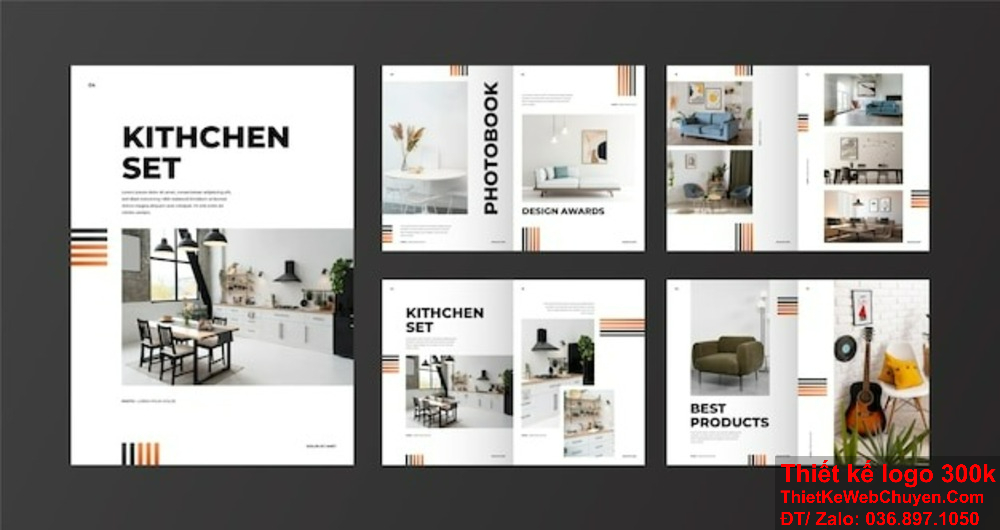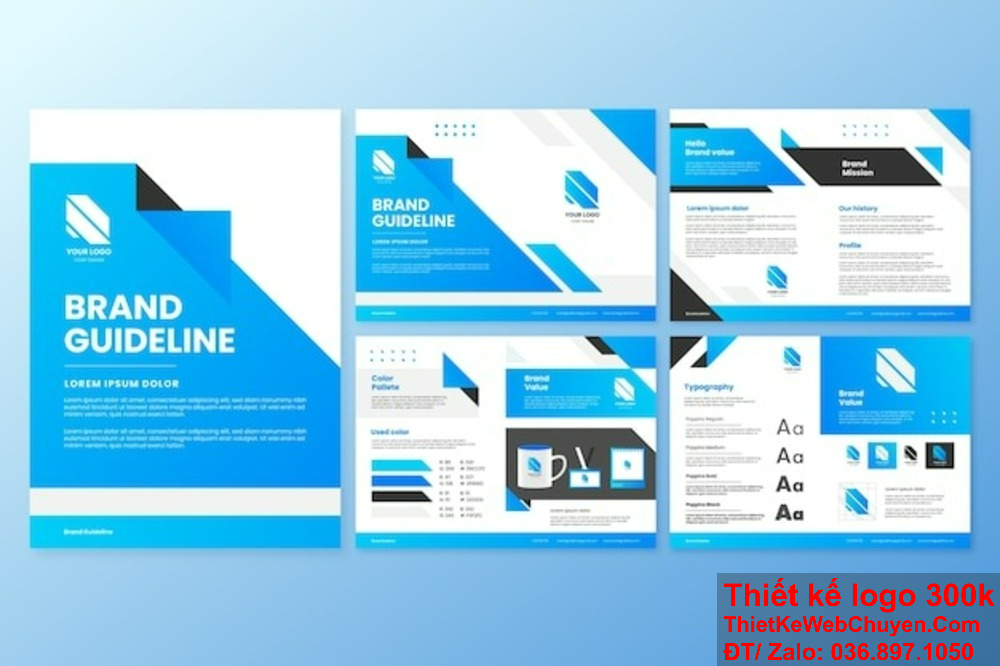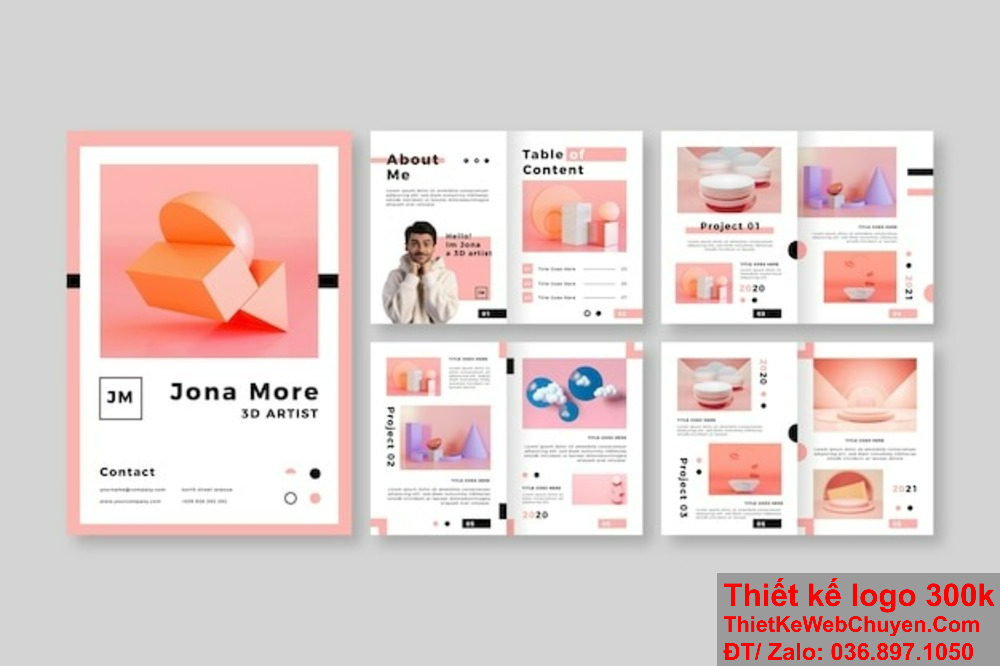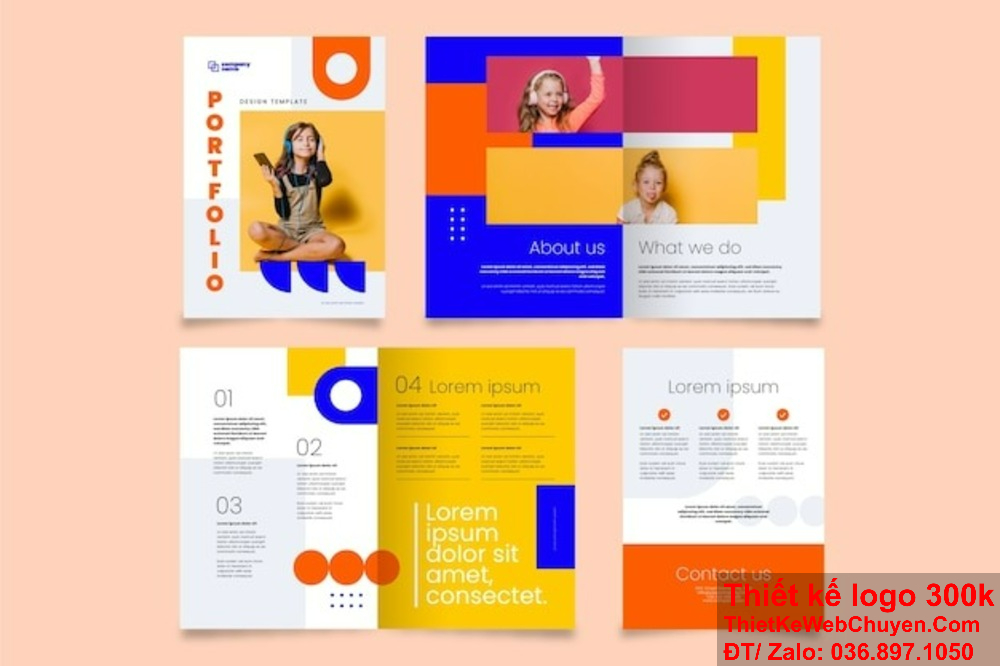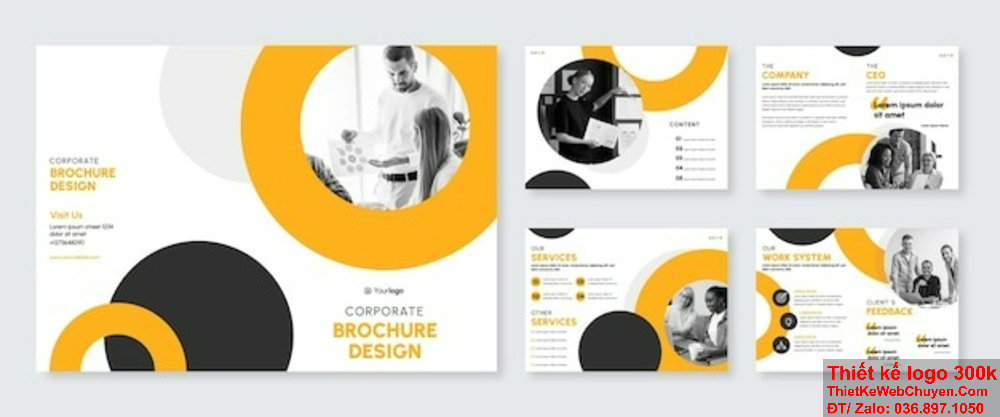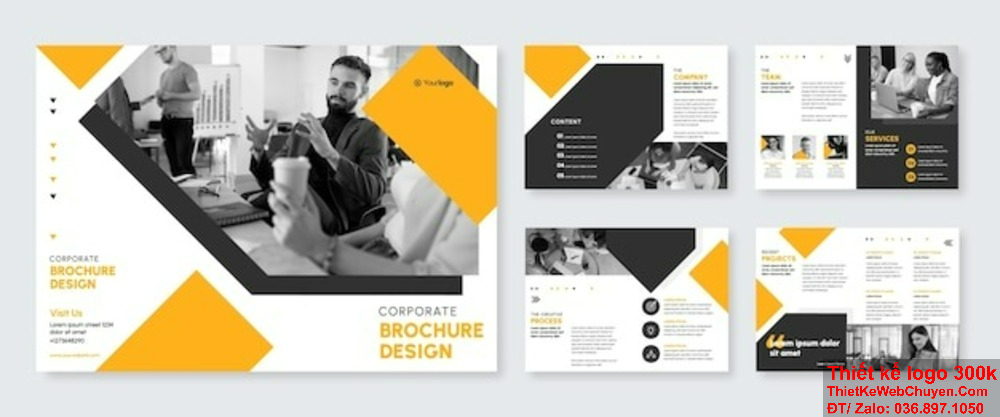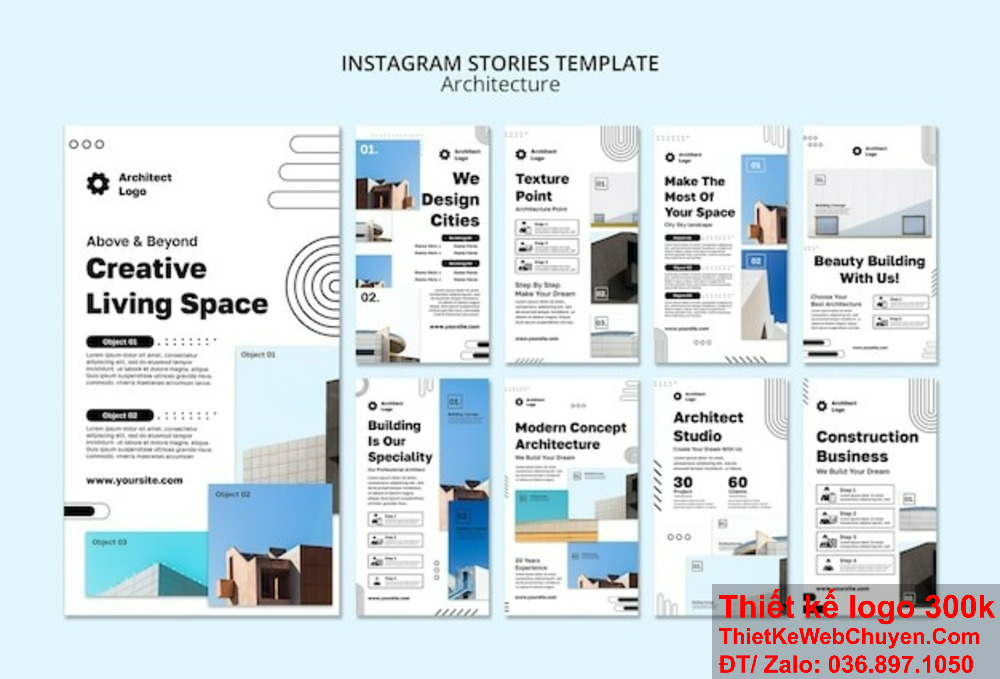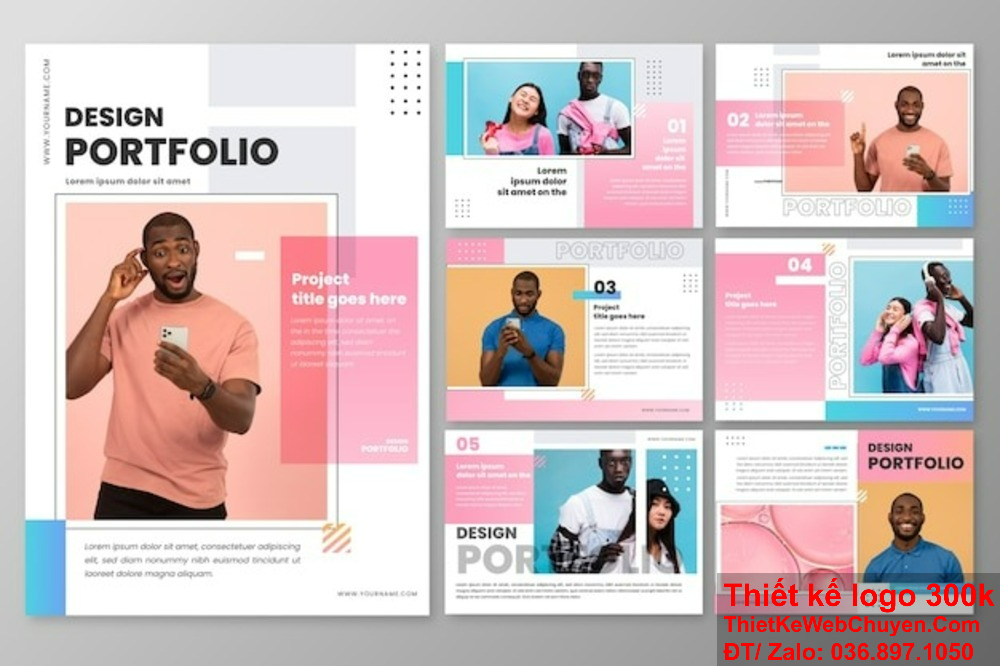
Font chữ trong thiết kế profile đóng vai trò quan trọng trong việc thiết kế profile, đó là cầu nối giữa nội dung và người xem, góp phần quyết định về ấn tượng ban đầu. Font chữ trong thiết kế profile không chỉ đơn thuần là những ký tự trên màn hình mà còn là ngôn ngữ thị giác, truyền đạt không chỉ thông điệp mà còn cả tâm trạng và cá nhân của người sử dụng font chữ trong thiết kế profile.
Giới Thiệu Chủ Đề Font Chữ Trong Thiết Kế Profile
Đầu tiên, font chữ trong thiết kế profile có thể được định nghĩa như bộ ký tự chung với kiểu dáng và đặc tính nhất định. Mỗi font chữ trong thiết kế profile mang đến một cái nhìn riêng biệt, từ những đường cong mềm mại của serif đến sự hiện đại và gọn gàng của sans-serif. Vai trò của font không chỉ giới hạn ở khả năng truyền đạt thông điệp mà còn mở rộng đến việc tạo nên sự chuyên nghiệp, sáng tạo, hay thậm chí là tính cá nhân của người sử dụng profile.
Sự ảnh hưởng của font là không thể phủ nhận. Ngay từ cái nhìn đầu tiên, font chữ trong thiết kế profile tạo ra ấn tượng mạnh mẽ và nhanh chóng hình thành một hình ảnh về người sử dụng. Sự chọn lựa cẩn thận về font chữ trong thiết kế profile có thể nói lên tính cách, phong cách và mục tiêu của cá nhân đó. Một font phù hợp không chỉ làm tăng giá trị thẩm mỹ mà còn là yếu tố quyết định sự chuyên nghiệp và độ chân thực của thông điệp được truyền đạt.
Tổng kết, font chữ trong thiết kế profile là một phần không thể thiếu trong việc xây dựng hình ảnh cá nhân trên các nền tảng trực tuyến. Từ việc chọn lựa kiểu dáng đến màu sắc, mỗi quyết định về font đều ảnh hưởng đến cách mà người xem đánh giá và nhớ đến một profile. Chính vì vậy, hiểu rõ và sử dụng đúng font chữ trong thiết kế profile là chìa khóa để tạo nên một ấn tượng mạnh mẽ và lâu dài trong không gian trực tuyến ngày nay.
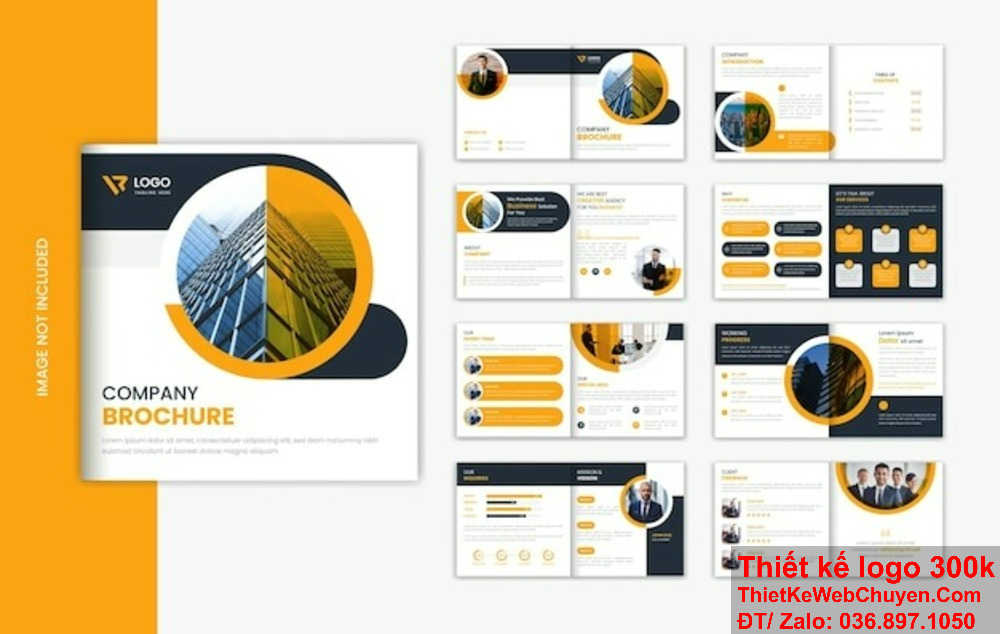
Lịch Sử Phát Triển Font Chữ Trong Thiết Kế Profile
Lịch sử phát triển font là một hành trình đầy màu sắc và sáng tạo, từ những bước đầu tiên của chữ viết tay đến sự đa dạng và phong phú của font chữ trong thiết kế profile kỹ thuật số ngày nay. Các bước quan trọng trong lịch sử này đã ảnh hưởng đến cách chúng ta hiểu và sử dụng font.
Bắt đầu từ thời kỳ cổ điển, font chữ trong thiết kế profile yếu được tạo ra thông qua việc viết tay. Đây là thời kỳ của những bức thư và tài liệu chính thức được soạn thảo bằng bàn tay tài năng của các nghệ sĩ viết chữ. Tuy nhiên, sự đòi hỏi về tốc độ và khả năng nhân bản đã thúc đẩy sự phát triển của các kiểu chữ in ấn đầu tiên.
Trong thời kỳ công nghiệp, máy in chữ đã xuất hiện, mở ra kỷ nguyên mới trong việc sản xuất và phân phối sách báo. Điều này tạo nên sự đa dạng hóa về kiểu chữ, từ serif truyền thống đến xu hướng sans-serif tiện ích. Đến thập kỷ 20, sự phổ biến của máy tính và công nghệ số hóa đã mở ra cánh cửa cho font chữ trong thiết kế profile kỹ thuật số, nơi mà người thiết kế có thể tạo ra và tùy chỉnh font một cách linh hoạt và sáng tạo.
Sự thay đổi và xu hướng trong việc sử dụng font chữ trong thiết kế profile qua các thời kỳ phản ánh cả những biến động xã hội, văn hóa và kỹ thuật. Từ sự tinh tế của chữ serif trong thời kỳ quốc gia hoá, đến sự đơn giản và hiện đại của chữ sans-serif trong thời đại công nghiệp, mỗi thời kỳ mang lại một cái nhìn mới về vẻ ngoại hình và cảm nhận về thông điệp.
Tóm lại, lịch sử phát triển font là một cuộc hành trình không ngừng, đưa chúng ta từ chữ viết tay cổ điển đến sự đa dạng và linh hoạt của font chữ trong thiết kế profile kỹ thuật số hiện đại. Hiểu rõ lịch sử này giúp chúng ta có cái nhìn sâu sắc hơn về tầm quan trọng của font chữ trong thiết kế profile trong việc thể hiện cá nhân và tạo nên ấn tượng trong thiết kế profile.
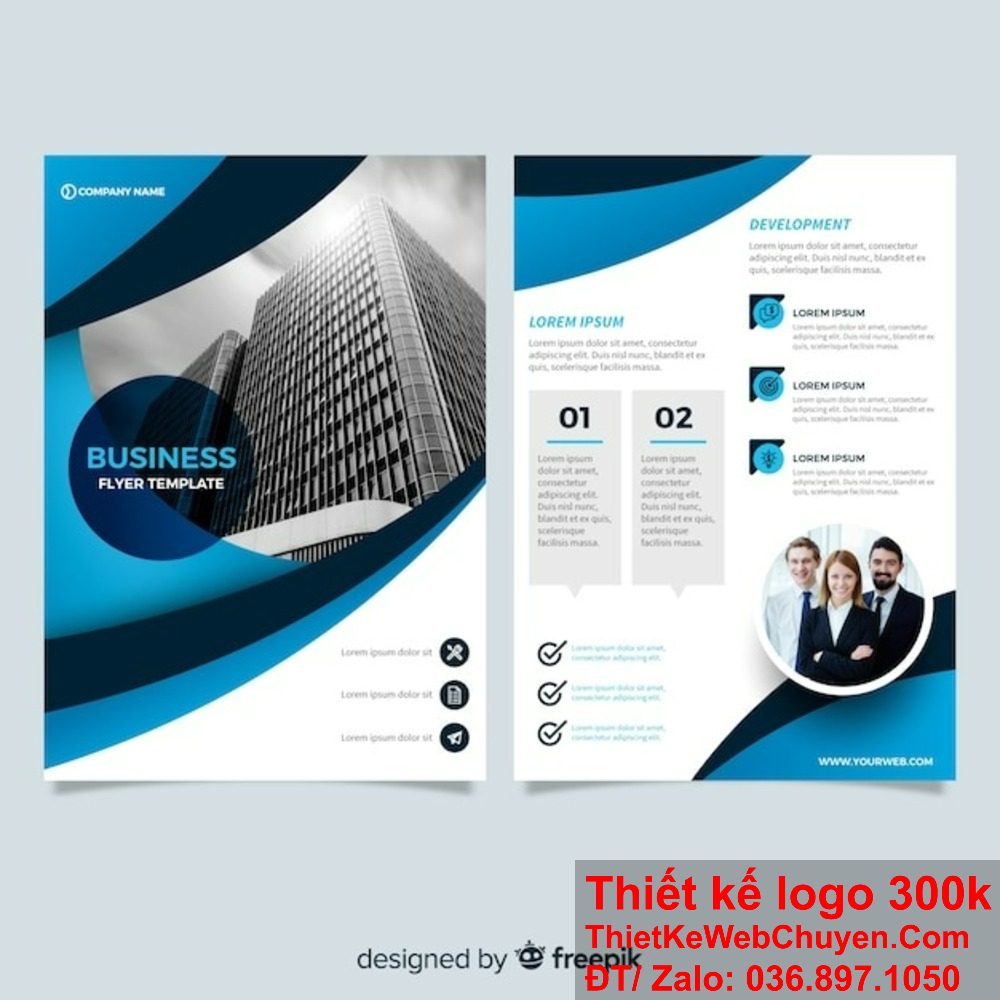
Phân Loại Font Chữ Trong Thiết Kế Profile
Trong thế giới đa dạng của font chữ trong thiết kế profile, sự phân loại chính là yếu tố quyết định cách mà một thông điệp được truyền đạt. Có bốn loại font chữ trong thiết kế profile chính đó là serif, sans-serif, script và decorative.
- Serif
– Giới thiệu Font chữ serif được nhận biết bởi những nét đường kết cấu và những “chấm” hay “nút” tại đỉnh hoặc đáy của các chữ cái. Đây thường là font chữ trong thiết kế profile truyền thống và chuyên nghiệp.
– Ảnh hưởng Serif thường tạo ra một cảm giác truyền thống, tôn vinh và nghiêm túc. Chúng thích hợp cho những profile liên quan đến lĩnh vực văn phòng, pháp luật hay tài chính.
- Sans-serif
– Giới thiệu Ngược lại với serif, font chữ trong thiết kế profile sans-serif không có các “chấm” hay “nút” ở đỉnh và đáy. Chúng thường mang đến vẻ hiện đại và sáng tạo.
– Ảnh hưởng Sans-serif thường được sử dụng trong những bản thiết kế mang tính chất đương đại và thân thiện. Chúng thích hợp cho các profile liên quan đến công nghệ, nghệ thuật và thiết kế.
- Script
– Giới thiệu Font chữ script thường mang đến cảm giác của việc viết tay. Chúng có các đường nét cong và có thể biến đổi tùy thuộc vào kiểu dáng.
– Ảnh hưởng Script thường tạo ra một cảm giác cá nhân và ấm áp, thích hợp cho những người muốn truyền đạt tính cách cá nhân và sự tương tác.
Cuối cùng, trong một thế giới số hóa ngày càng đa dạng, font chữ trong thiết kế profile không chỉ là yếu tố thiết kế mà còn là ngôn ngữ của sự biểu đạt và tương tác trực tuyến. Việc chọn lựa và kết hợp font chữ trong thiết kế profile không chỉ là nghệ thuật mà còn là khoa học, làm nổi bật không gian cá nhân và sự sáng tạo của mỗi người trên mạng xã hội và các nền tảng truyền thông số. Font chữ trong thiết kế profile, với tất cả đặc tính và tiềm năng, tiếp tục là nhân tố quan trọng, làm nổi bật sự độc đáo và cá nhân hóa trong thế giới kỹ thuật số hiện nay.